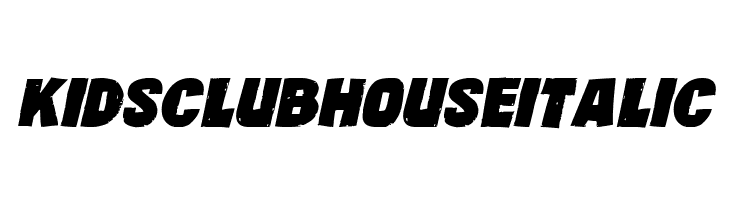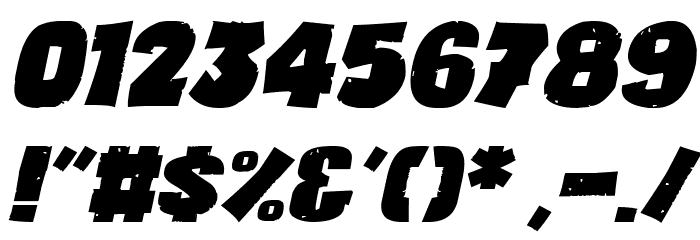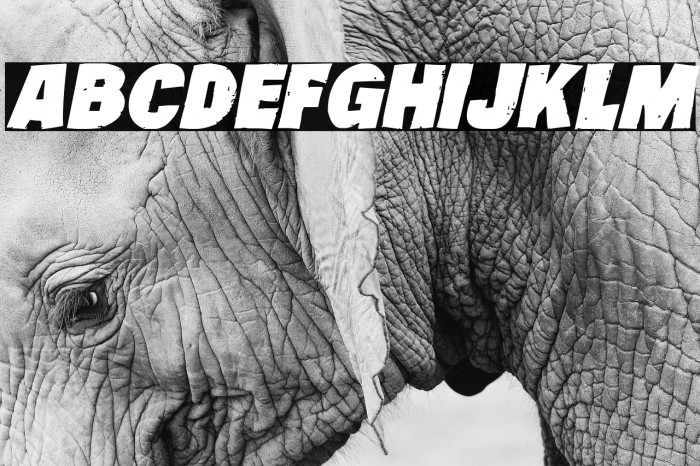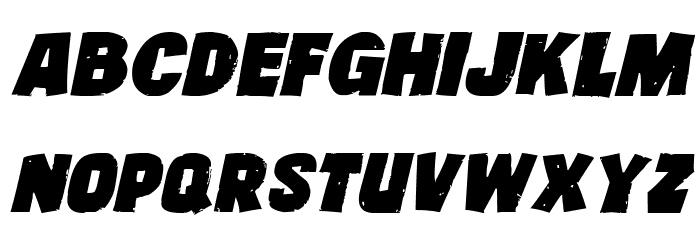
Kids Club House Italic Font
✎ Cartoon
| Stile generale | Playful, Energetic, Rugged |
| Progetti proposti | Perfect for children's book covers, playful posters, adventure-themed branding, and dynamic social media graphics. |